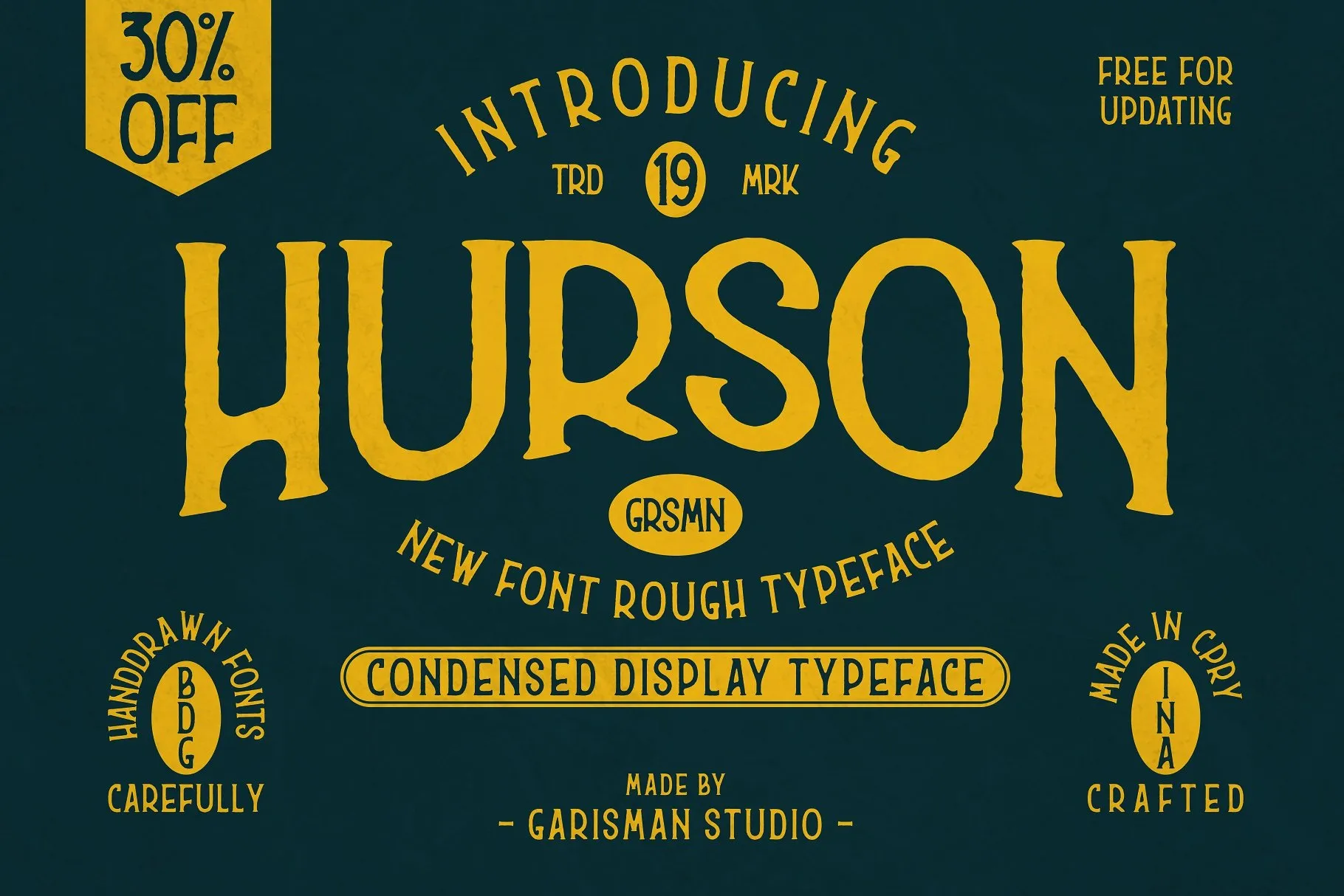
Hurson Typeface – Download Grátis
A fonte ‘Hurson Typeface’ é uma tipografia retrogama com aparência retrô clara, elegante e sofisticada, inspirada em estilos manuscritos femininos e agradáveis. Suas linhas são finas, proporcionando um aspecto elegante e delicado que transmite beleza e estilo. Desenvolvida por M.0Type, esta fonte incorpora elementos vintage e clássicos, com uma aparência manufaturada, como se fosse uma criação do passado. Ela é perfeitamente adaptável para designs de identidade visual, desde materiais de marca até logotipos, cartões de visita, posters e camisetas. Suas características PUA (Unicode) permitem a integração sem problemas em qualquer sistema gráfico, tornando-a uma escolha excelente tanto para designers profissionais quanto para iniciantes que desejam adicionar um toque vintage às suas criações. Ideal para design de logo, t-shirts personalizadas e até mesmo para aplicar nas fotografias ou slogans.